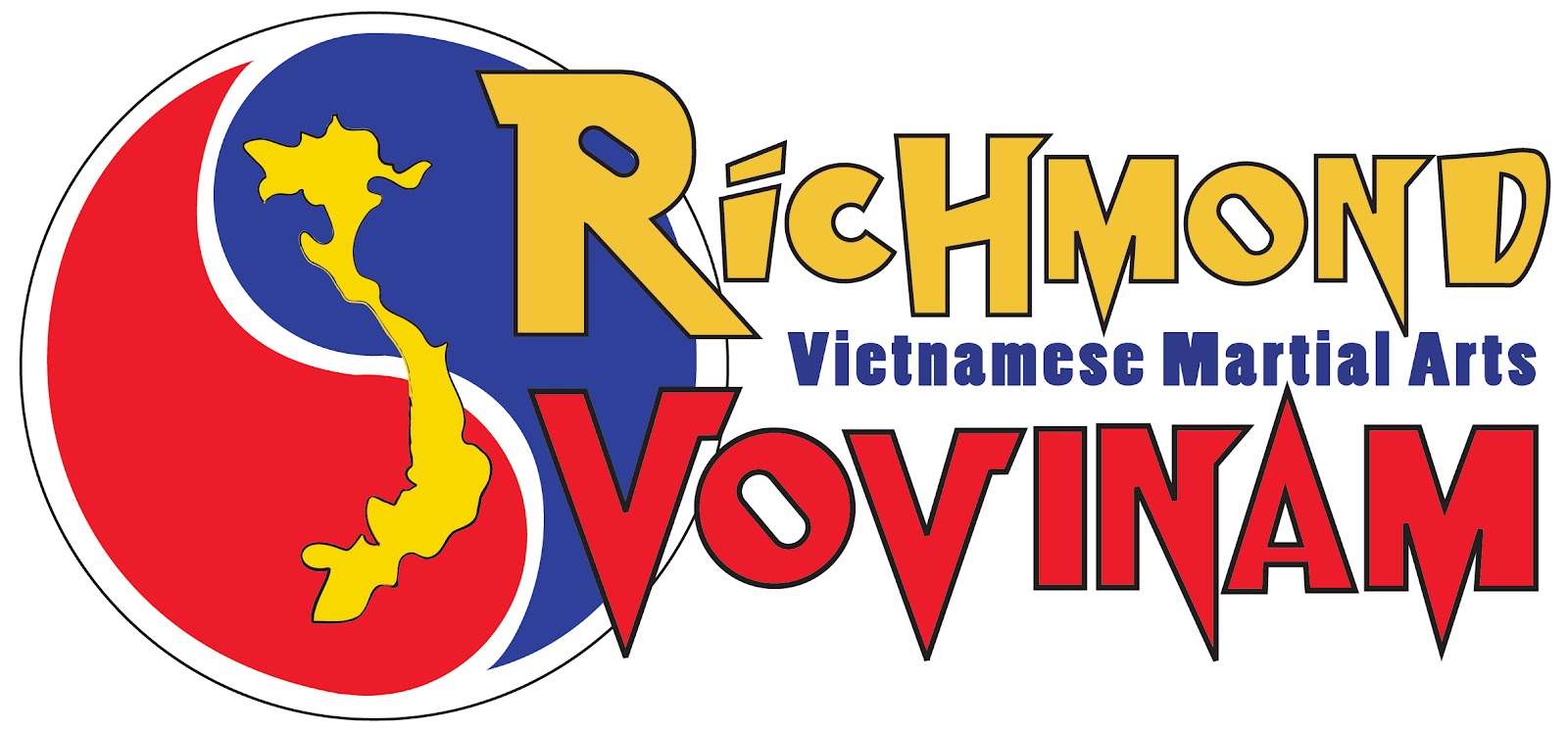
Hỏi có font nào như chữ "khoan cắt bê tông" giống hình ko cho xin :D:D:D ko thì tut hay gì gì đó cũng được. Thanks
Pro nào có font walking dead này cho em xin với ERPkRkM.jpg
@ĐạiTrần ,Mình nghĩ là font sfu helvenicanue hoặc utm avo hoặc utm americana
3 font trên đều có nét mỏng như trên
cho mình hỏi cái chữ "Gia Phan" này là font gì thế nhỉ
mấy cái hình của thớt đấy k phải là Font nha.
đó chỉ là Typography, mà Typography k có sẳn đâu. =)))
Các bác cho em hỏi font này là font gì với ạh. Em tìm đủ các kiểu (google, tìm bằng ảnh...) rồi mà không ra, bác nào thấy qua thì cho em xin cái tên với ạh. Thanks các bác nhiều. ​
Chào các bác, mình mới xem phim ngắn Làm Cha của em Hoài Lâm (
). Ngoài màu sắc trong phim thì mình rất rất thích font chữ chữ "Hoài Lâm " và chữ "Làm cha" ở đầu phim :x:x:x nên lập hẳn topic để hỏi. Không biết có bác nào biết font chữ ý tên là gì ko ạ ? hoặc có bác nào tốt bụng có font chữ đó cho mình xin được không ạ :x:x:x . Cảm ơn các bác nhiều :*:*:*
cho em xin font này với ạ :P
chào các bạn, mong nhờ các bạn tìm giúp mình font chữ của ledock giùm mình, mình xin chân thành cảm ơn các bạn rất nhiều, xin chân thành cảm ơn
Như trên chủ đề, bác nào có cho em xin 2 tên font đó, về em làm logo cho thằng bạn
Cho mình xin font Avenir dạng unicode để gõ tiếng việt hoặc họ của chúng dc ko bạn :)
Nhân tiện bạn nào thich font họ Futura thì ới nhé, mình có bộ type unicode ngon lành.
Mọi người chỉ giúp mình font này với. Cảm ơn mọi người rất nhiều
Dựa vào hướng dẫn của bạn Phạm Hữu Dư, tôi đã tìm ra được ffont của chữ gift card tên là Noa Pro Condensed nhưng tôi không tìm được font này đã hỗ trợ Tiếng Việt. Bạn nào trong diễn đàn có biết font này được Việt hóa xin chỉ giúp tôi.
Cho em xin font chữ trong clip này với ạ.
Em thấy font này intel và microsoft rất hay sử dụng
cho em hỏi kiểu chữ này là font hay vẽ vậy?